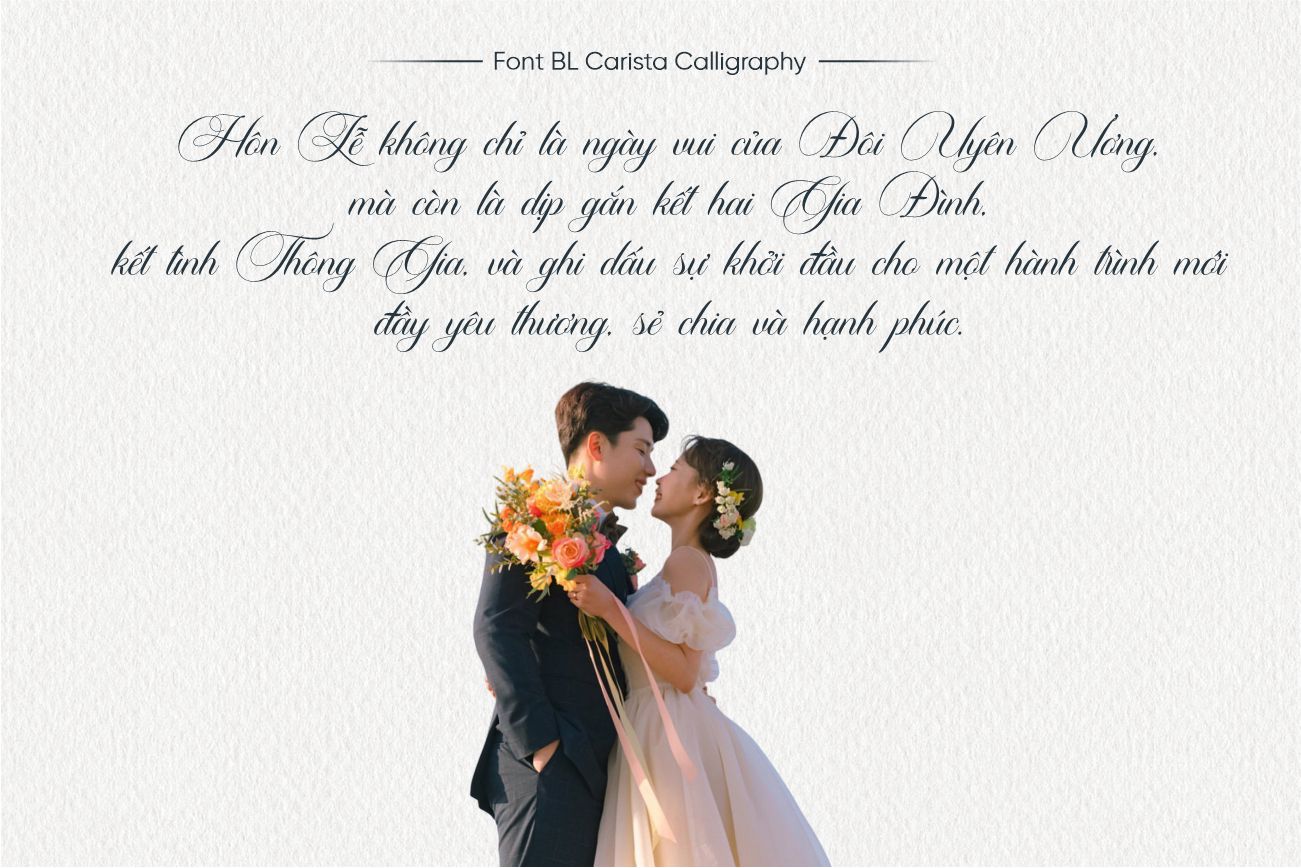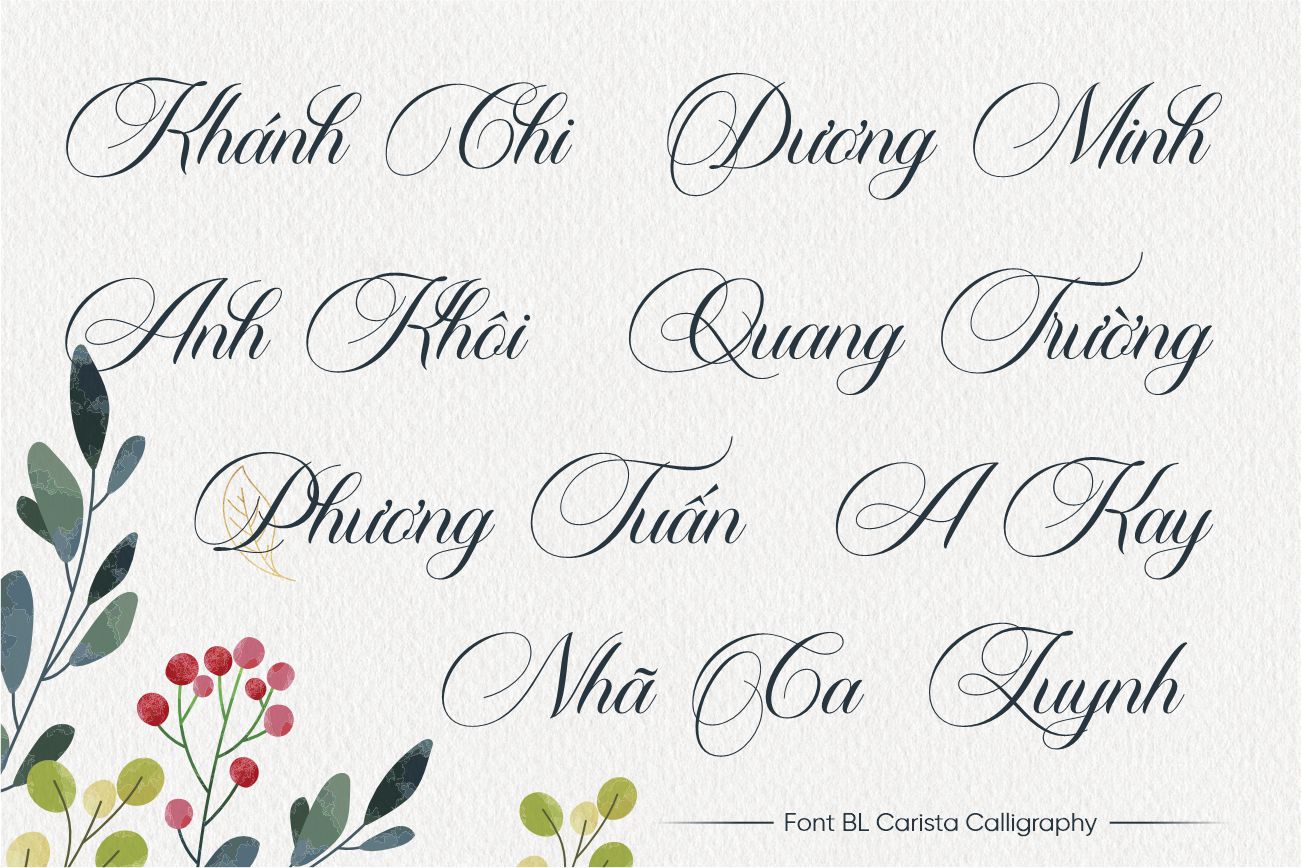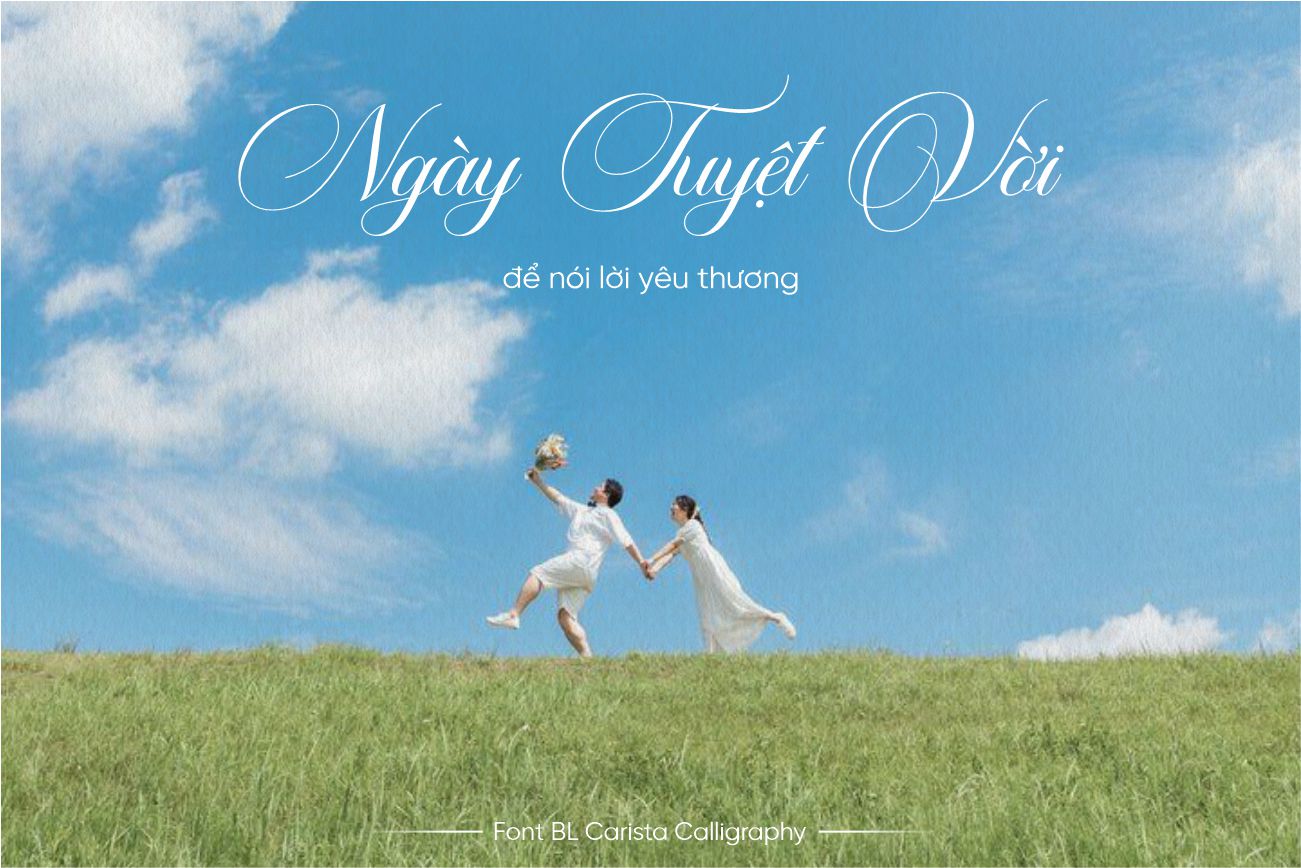
Phông chữ nghệ thuật sang trọng cho thiệp cưới - BL Carista Calligraphy
Trong lĩnh vực thiết kế sáng tạo, việc tìm kiếm một bộ chữ có khả năng chạm đến cảm xúc người xem luôn là ưu tiên hàng đầu. BL Carista Calligraphy — một sản phẩm được Team BL Việt hóa từ bản gốc của nhà thiết kế Haikal Juanda — chính là viên ngọc quý dành cho những tâm hồn yêu cái đẹp. Bộ font này mang trong mình hơi thở đậm phong cách calligraphy sang trọng và bay bổng, biến mỗi dòng văn bản trở nên sống động như một bức họa thư pháp. Sự xuất hiện của BL Carista Calligraphy tại thị trường Việt Nam đã mang đến một lựa chọn hoàn hảo cho những dự án đòi hỏi tính thẩm mỹ cao và sự đầu tư kỹ lưỡng về mặt thị giác.
Điểm nhấn làm nên sức hút mãnh liệt của bộ chữ chính là những đường nét uốn lượn được tạo tác một cách tinh xảo và đầy nghệ thuật. Không giống như những phông chữ script thông thường, BL Carista Calligraphy sở hữu các nét thanh đậm biến chuyển linh hoạt, tạo nên một nhịp điệu thị giác vừa uyển chuyển vừa dứt khoát. Cấu trúc của các con chữ được liên kết chặt chẽ nhưng vẫn giữ được độ thoáng đãng, mang lại cảm giác lãng mạn khó cưỡng. Từng ký tự được chăm chút tỉ mỉ để khi đứng cạnh nhau, chúng tạo nên một dòng chảy tự nhiên, giống như những nét bút lông được đưa trên nền giấy lụa bởi những nghệ nhân bậc thầy.
Nguồn gốc của font chữ bắt nguồn từ mong muốn của Haikal Juanda trong việc tái hiện lại vẻ đẹp cổ điển của nghệ thuật viết tay truyền thống trong môi trường kỹ thuật số hiện đại. Sự kết hợp giữa kỹ thuật đồ họa tân tiến và cảm hứng từ các bản thảo cổ điển đã tạo ra một bộ font mang linh hồn riêng biệt. Khi được Team BL thực hiện Việt hóa, các dấu tiếng Việt được điều chỉnh một cách khéo léo để đảm bảo tính đồng nhất tuyệt đối. Nhờ vậy, bộ chữ vẫn giữ trọn vẹn nét tinh xảo và đầy nghệ thuật, đồng thời phục vụ tốt nhất cho các nhà thiết kế Việt trong việc truyền tải thông điệp một cách chuyên nghiệp và ấn tượng.
Với những đặc điểm ưu việt đó, BL Carista Calligraphy thường là lựa chọn ưu tiên cho các thiết kế thiệp cưới cao cấp, bìa sách văn học hay hệ thống nhận diện thương hiệu spa và mỹ phẩm. Sự hiện diện của nó giúp cho không gian thiết kế trở nên lãng mạn và có chiều sâu hơn bao giờ hết. Đặc biệt, khi được sử dụng làm tiêu đề cho các ấn phẩm nghệ thuật, bộ font với đậm phong cách calligraphy sang trọng và bay bổng này sẽ lập tức tạo ra sự khác biệt, giúp nâng tầm giá trị của toàn bộ tác phẩm trong mắt công chúng và đối tác.
BL Carista Calligraphy không chỉ đơn thuần là một kiểu chữ, mà là một ngôn ngữ của cái đẹp và sự tinh tế. Sự tận tâm trong quá trình Việt hóa của Team BL đã giúp cộng đồng thiết kế có thêm một công cụ tuyệt vời để hiện thực hóa những ý tưởng bay bổng nhất. Dù ở bất kỳ bối cảnh nào, bộ font này cũng luôn chứng minh được giá trị của mình nhờ vẻ ngoài tinh xảo và đầy nghệ thuật, góp phần tạo nên những dấu ấn khó phai trong lòng người xem qua từng nét chữ thanh cao và quý phái.